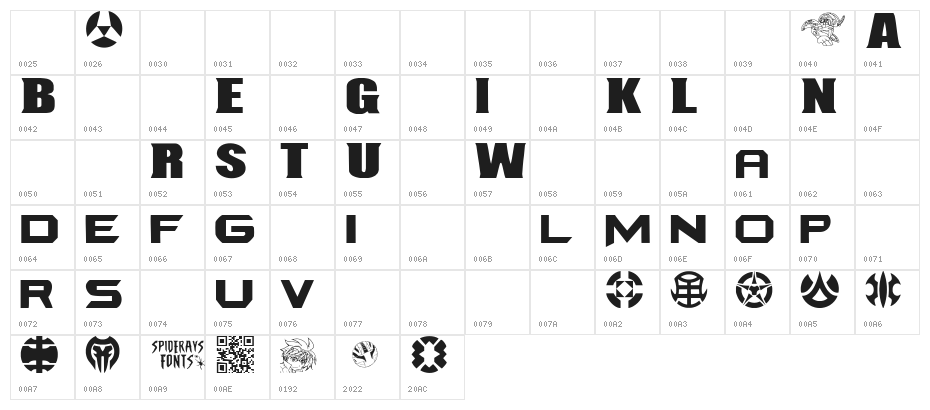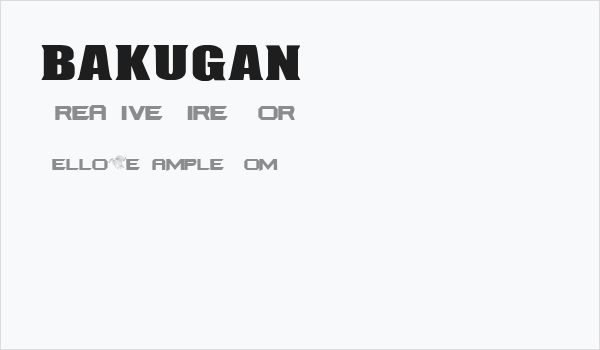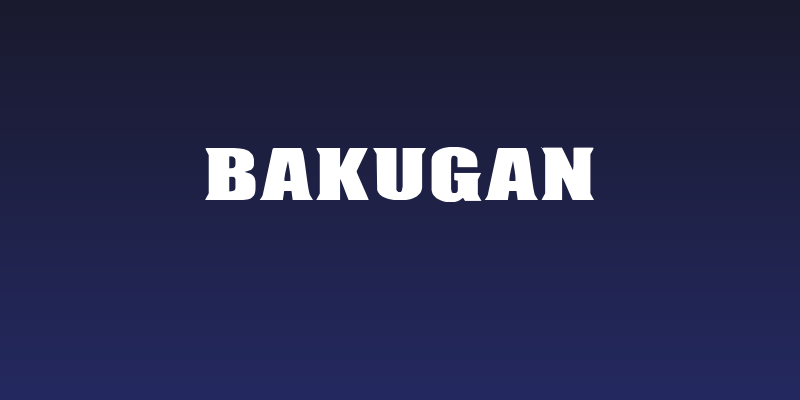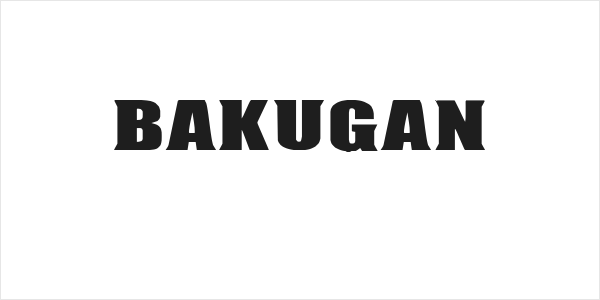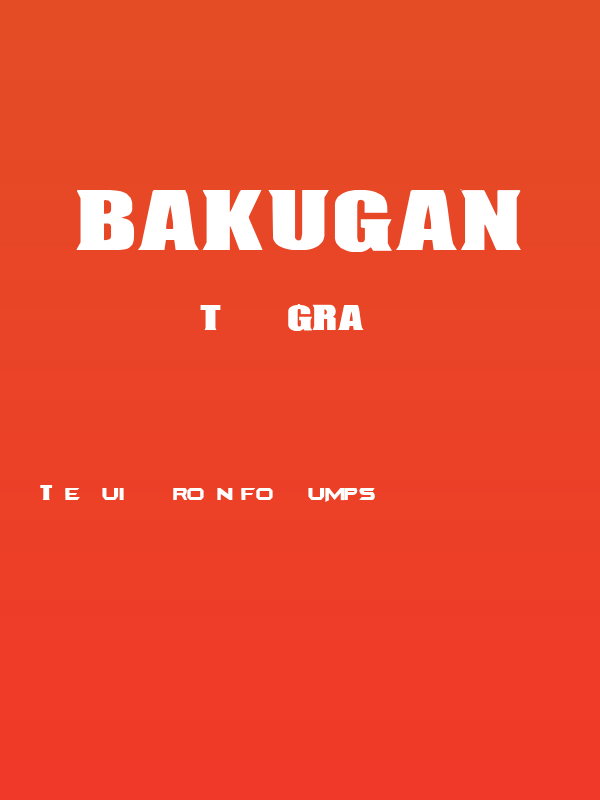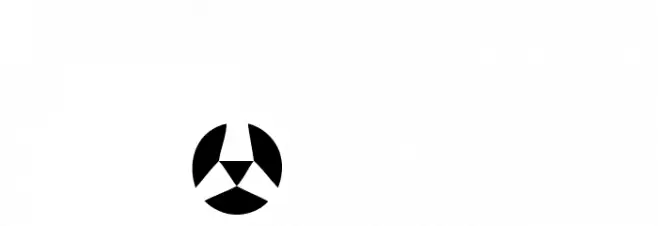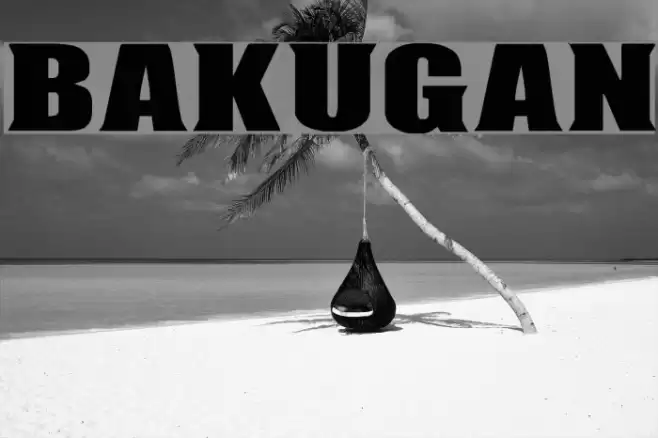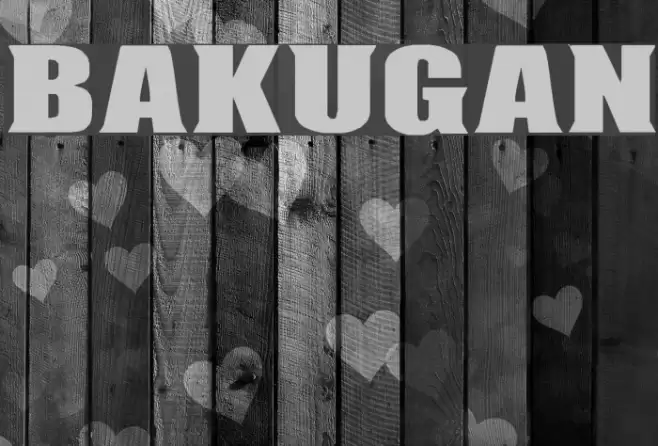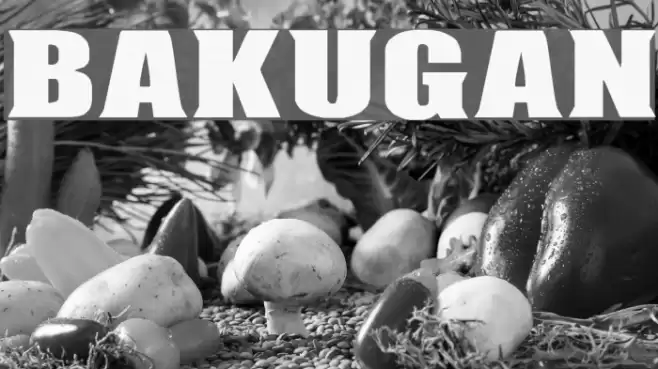
BAKUGAN Font
BAKUGAN
| 全体的なスタイル | Futuristic, Industrial |
| おすすめプロジェクト | Ideal for projects requiring a strong, futuristic aesthetic, such as technology branding, video game titles, or sci-fi movie posters. |